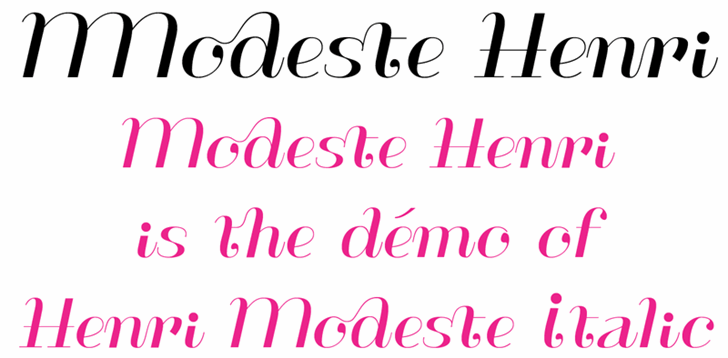
Aqui está uma versão em português do Brasil para a descrição de download da font ‘ModesteHenri’, adequada às instruções fornecidas: Na categoria de fonts Blackletter, encontramos ModesteHenri, um tipo criado pelo designer Hamilton. ModesteHenri é uma mistura de formas maiúsculas e minúsculas, com contrastes altos que adicionarão um toque eccentrico a seus documentos. Suas muitas ligaturas o tornam único, dando um aspecto peculiar aos textos em que você usá-lo. ModesteHenri é perfeito para quem busca uma fonte única e elegante, ou mesmo para aqueles que querem dar um toque diferente ao seu design gráfico. Se você está procurando por algo mais que o básico, ModesteHenri é uma ótima opção. Visite a página de download na URL fornecida para adquirir esta fonte irresistivelmente especial.